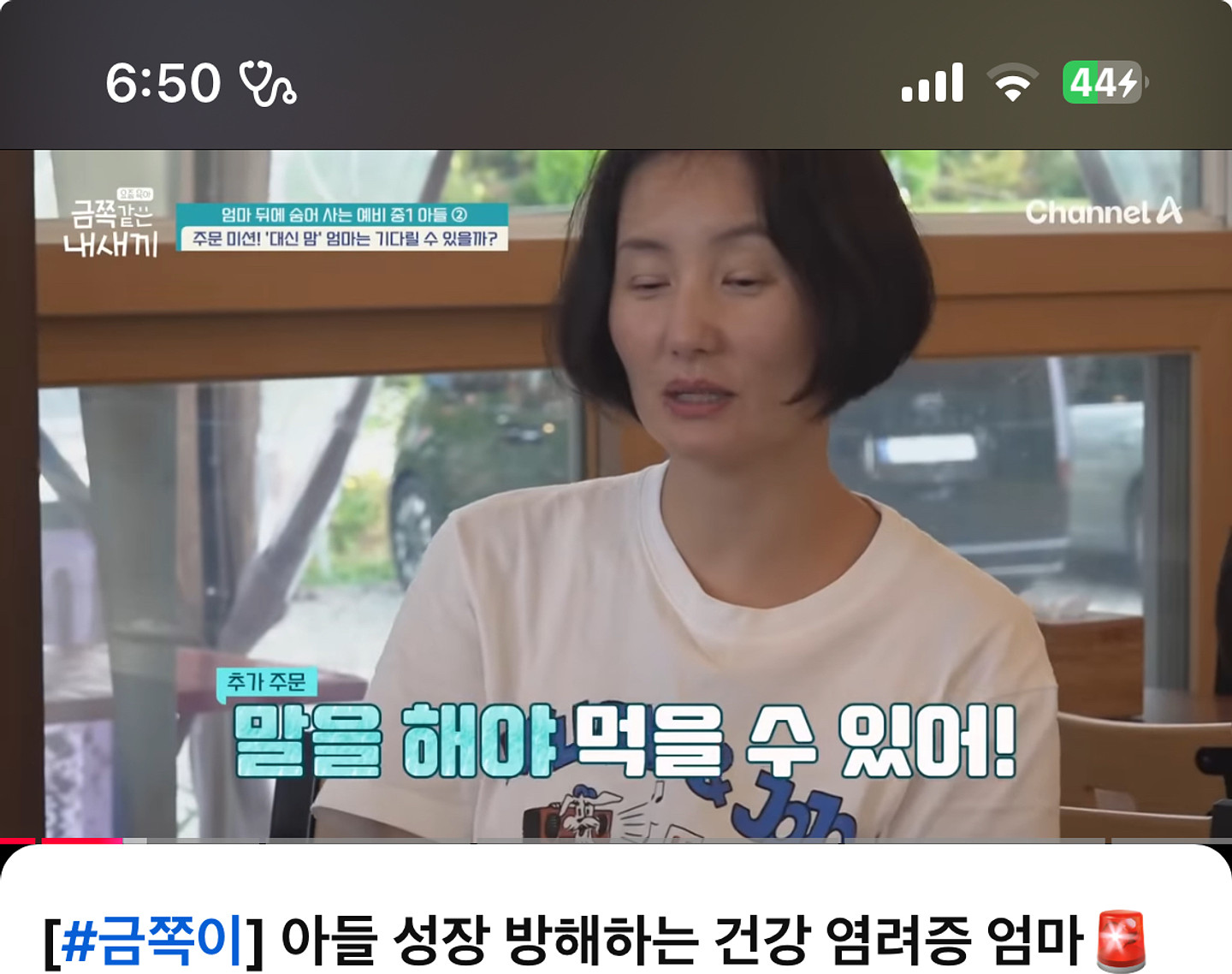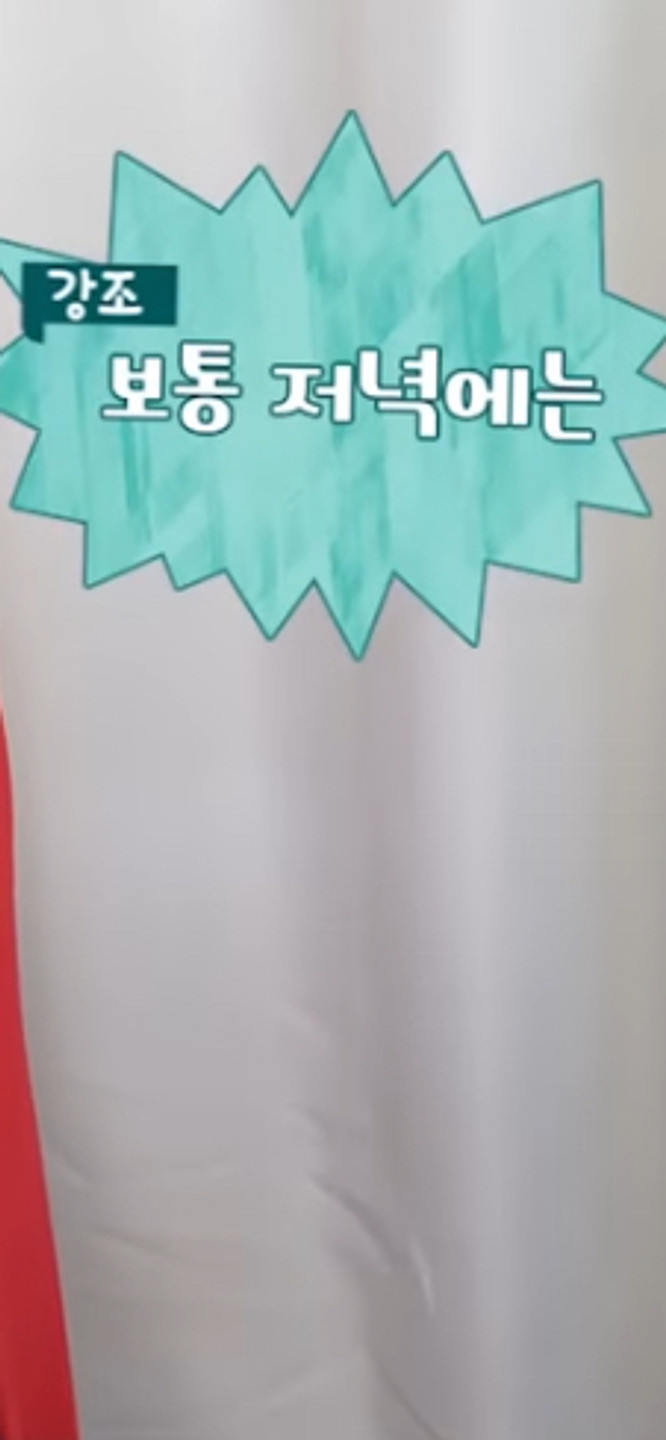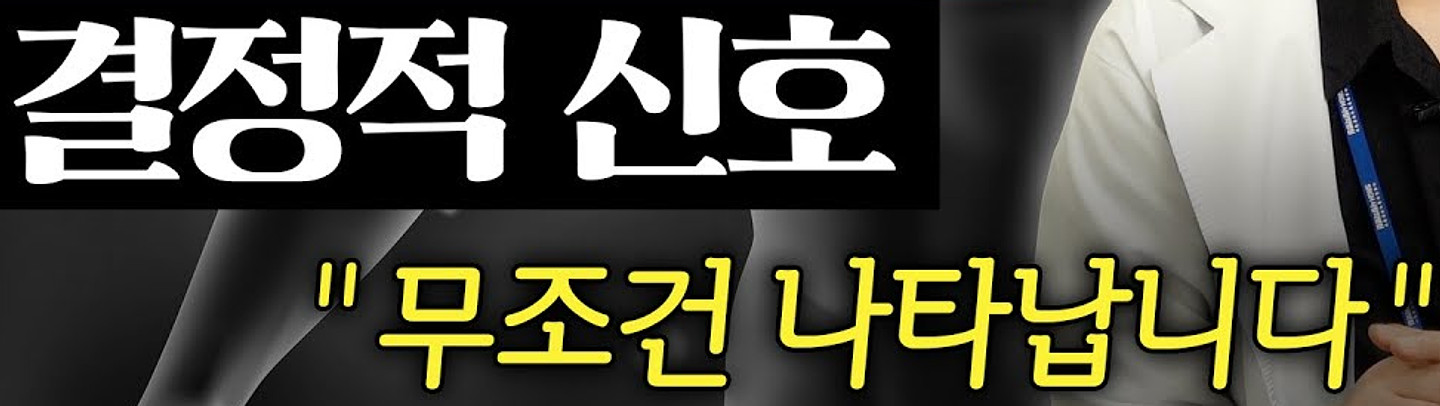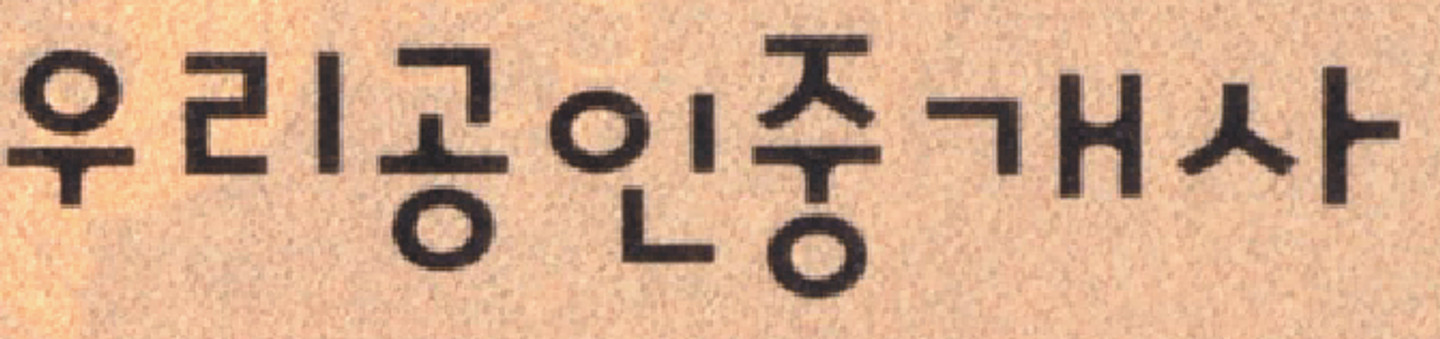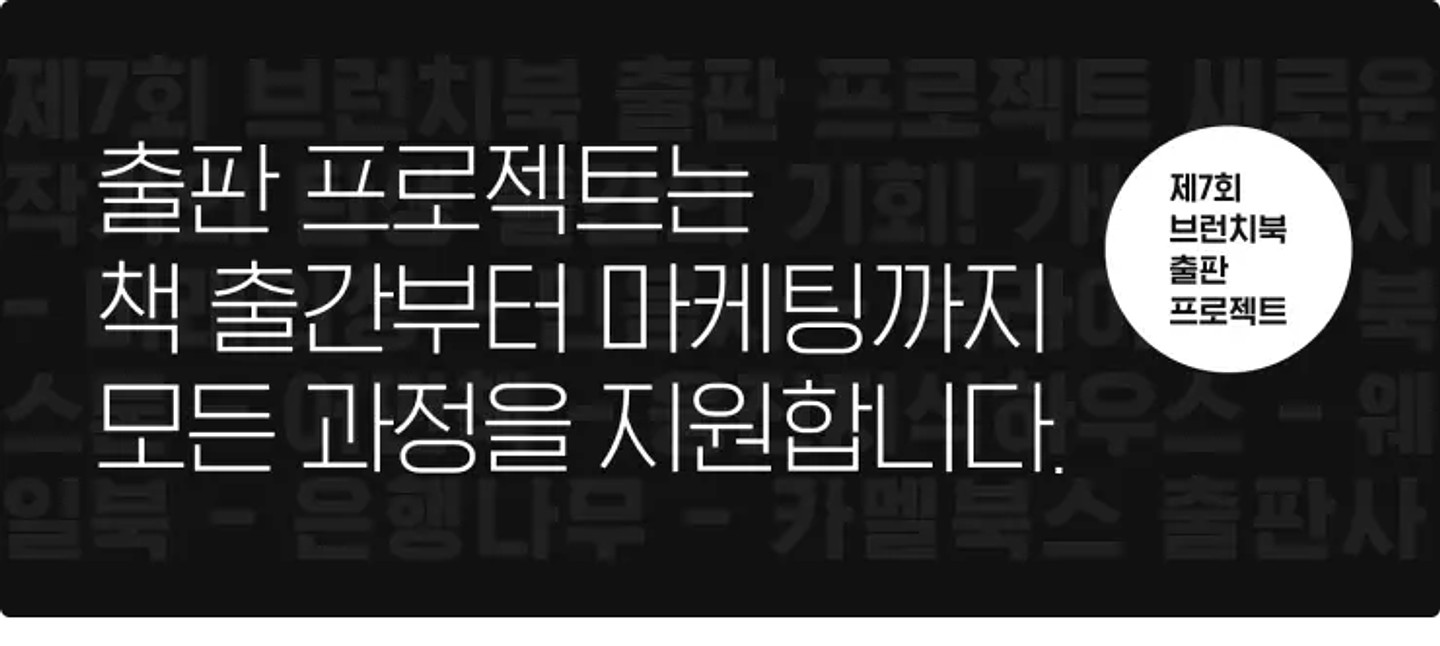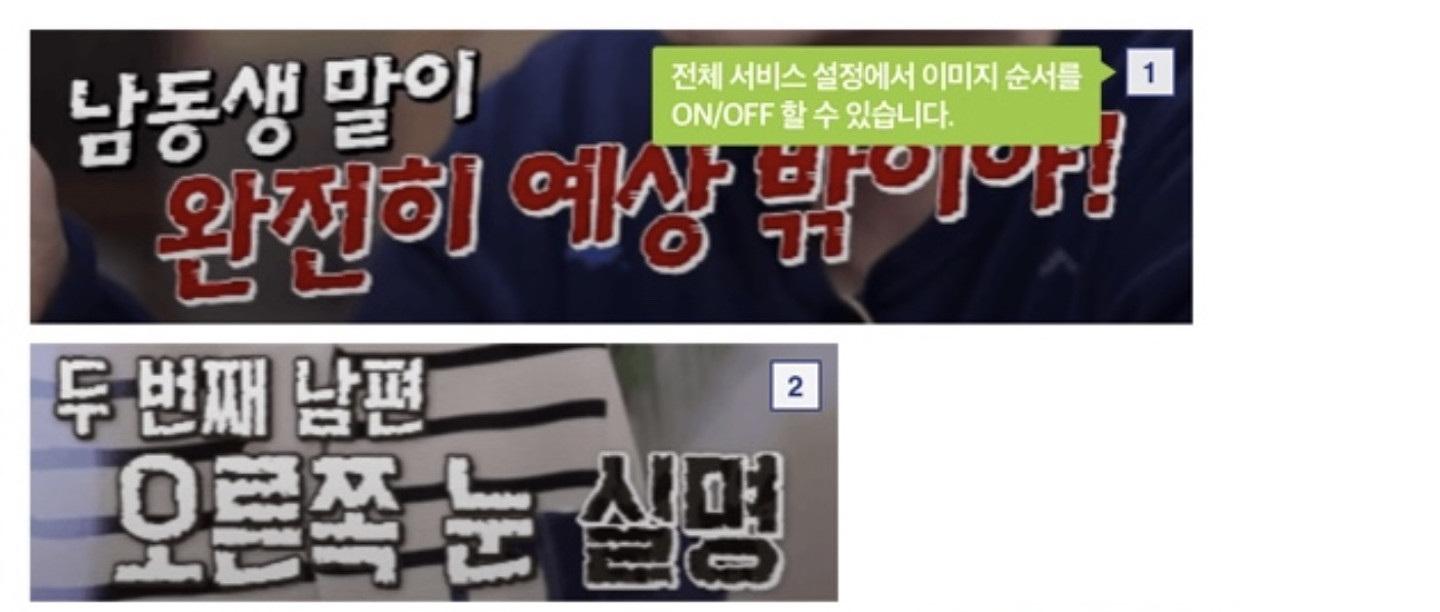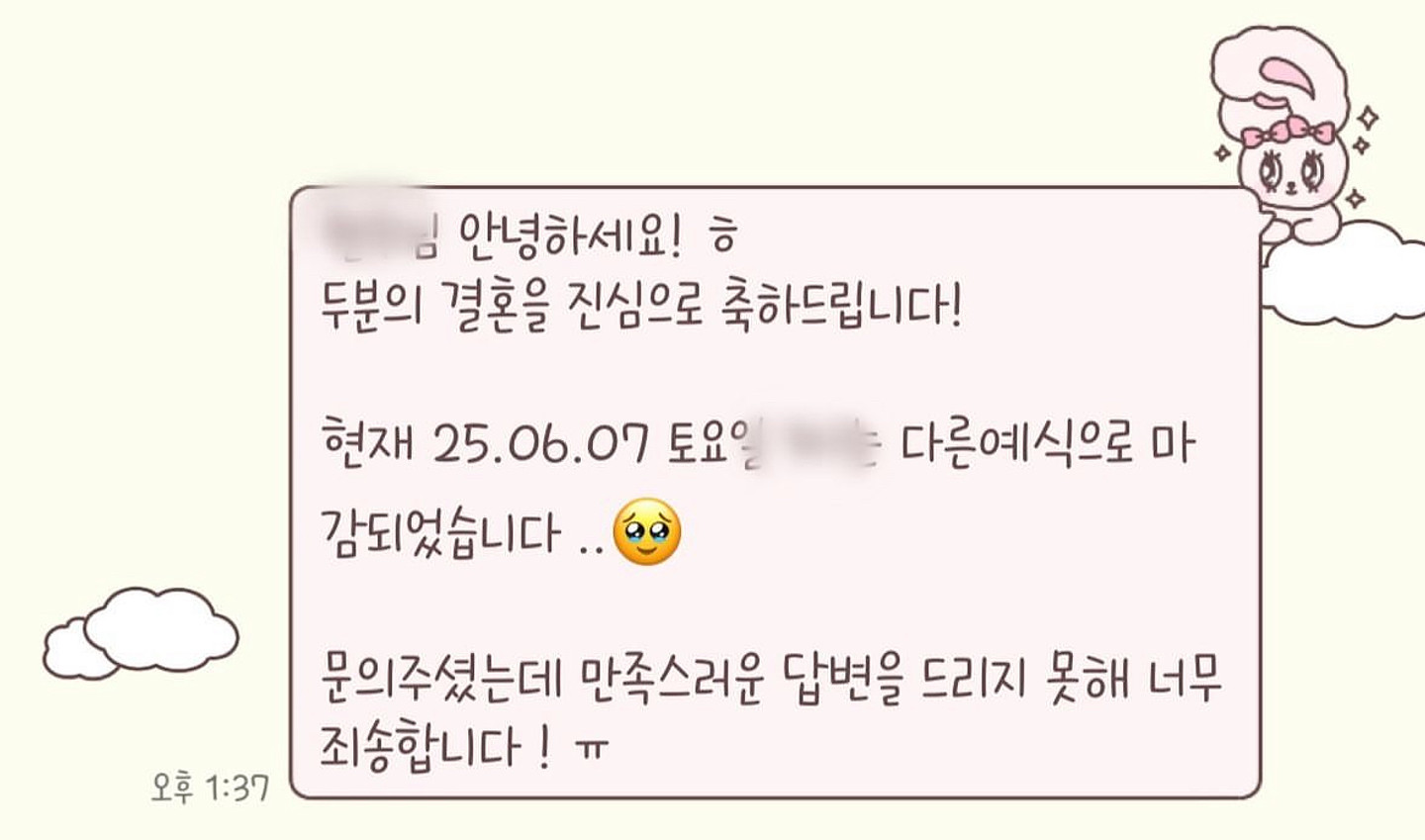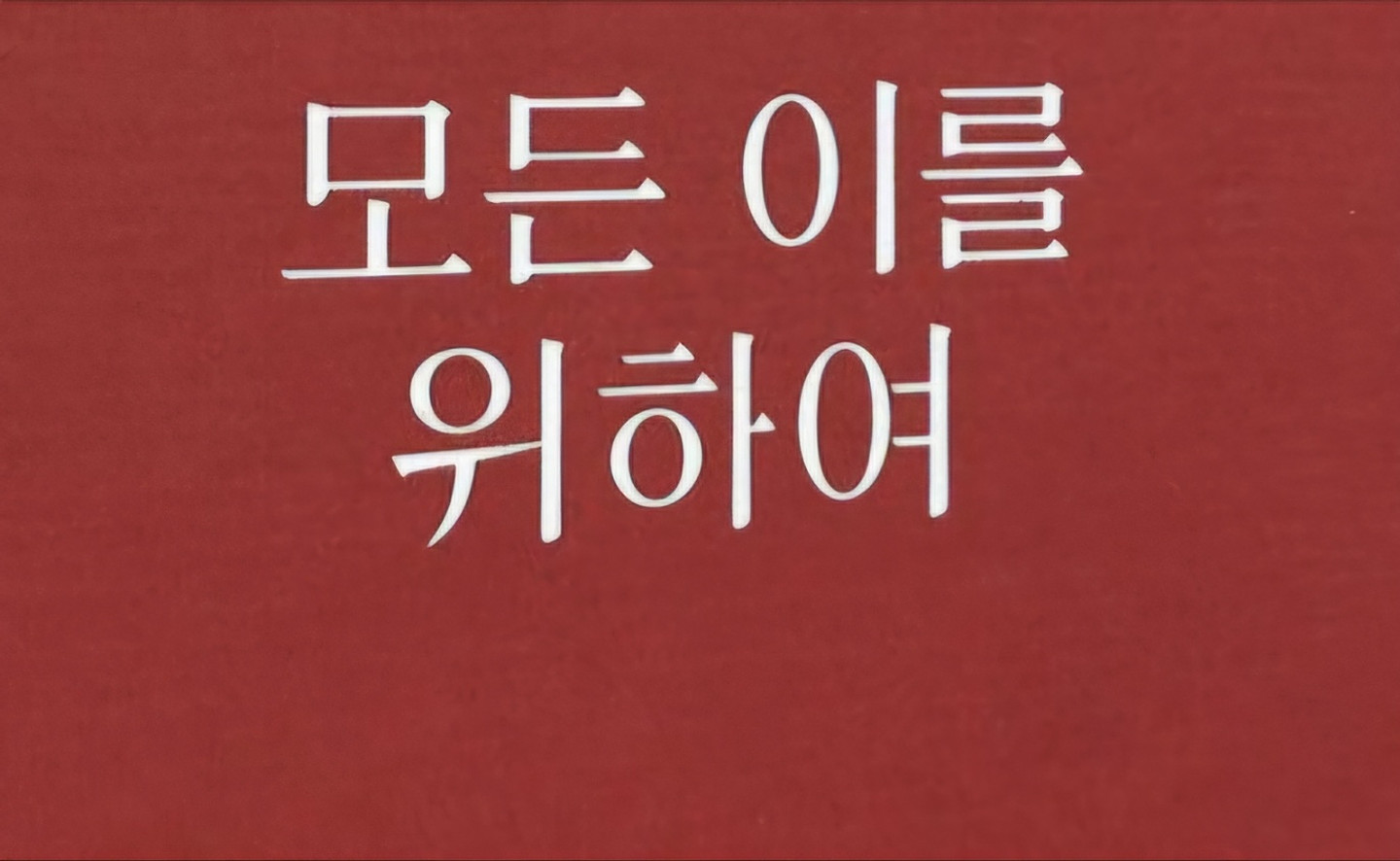
폰트 뭘까요>>
폰트 뭘까요
이거 무슨 폰트인지 알수있을까용 ?
인터넷보다가 본 짤인데 폰트가 너무 예뻐서 찾고싶어요
이건 무슨 폰트인가요??
너무 찾고 싶어요..산돌 검색해보니 안나오니 다른 브랜드 같아요.무슨 폰트인가요?ㅠㅠㅠ
바이오플라자 폰트 뭔가요~
이거 무슨폰트에여?
이 폰트는 무슨폰트일까요?
여기에 사용된 폰트 알려주세요ㅠㅠ
폰트가 몰까요..귀엽고 예뿌고 가독성 넘치네용
이 폰트명 알 수 있을까요?
요거 뭘까요?! ㅠㅠㅠㅠㅠ 급해용 ㅜ
인스타 썸네일에서 본 건데 이 폰트는 어떤 건가요?
무슨 폰트일까요?ㅠㅠ
해당 폰트 어떤 폰트일까요....급해요........
이 폰트 궁금합니다! 저렇게 획들이 크기가 다른 귀여운 폰트도 추천 부탁드려요!
혹시 이 폰트 뭘까요?
해당 영문 필기체 폰트가 무엇일까요... 아무리 찾아도 나오지 않네요...
무슨 폰트인지 아시는 분 계실까요?
폰트를 찾습니다 ㅠㅠ
폰트명이 고수님들 부탁드립니다
이게 무슨 폰트인가요ㅠㅜ알려주시면 정말 복 받으실거에요ㅠㅠㅠ
이거 무슨 폰트에여?
노포기에 나온 폰트인데 아시는 분 계실까요?
무슨 폰트인지 아시는 분 계신가요? 가운데는 편집한거겠죠?
이거 폰트 뭔지 아시는 분
알고 싶어요! 다운로드도 어디서 하는지!
알고 싶어요! 어디서 다운 받는지도!
이 폰트명이 뭔가요???
되게 특징적인데 ㅋ큐ㅠㅠ 못 찾고 있네요 산돌폰트 쪽인가 싶기도 하고요...
무슨 폰트일까요? 산돌 neo 시리즈랑은 미묘하게 다른듯 해 의견 구합니다
이거 폰트 어떤건지 알수있을까요? 예전에 자주 썻던건데 갑자기 이름이 생각이안나네요 ㅠㅠ 도와주세요
두산 명찰 폰트 뭔지 아시는 분 계신가요?
이 폰트 뭘까요...? 유튜브 썸네일에서 자주 보이던데. 귀여워서 궁금합니다! 도와주세용
유튜브 노래듣다가 본건데 이거 한글 무슨 폰트인가요?
이거 무슨 폰트야 ?
이름이 무엇인가요 급해요 ㅈㅂ
help me 20년전부터 있던 폰트 같은데...!!
이거 혹시 무슨 폰튼가요 대학 과제 중인데 너무 급해용
SSG 랜더스 등번호 폰트 뭔가요..? 최대한 비슷한거라도 알려주세요 ㅠㅠ
궁금해욧
무슨 폰트일까용...
안녕하세요 여기 폰트가 쥐마켓산스인줄 알았는데 아니더라구요....ㅠ 길쭉해서 자막으로 쓰기 좋은데 찾는 것을 함께 도와주실 귀인님들께 여쭙습니다 ㅠㅠ
이런 글씨체는 어디서 얻을수 있나요?? 궁금합니다 ㅠ
혹시 이 폰트 알고 계신분 계신가요?
무슨폰트일까요?? 궁금해요 알려주세요^^
출판만화 폰트인데 궁금합니다 ㅠㅠ
이 폰트 어떤 폰트일까요??
무슨폰트인지 아시는분
어떤 폰트일까요?ㅠㅠ 잘못 눌러서 폰트가 바뀌었는데 다시 찾으려니 못 찾아서요,,🥲
이건 무슨폰트인지 알려주실 수 있나요 ? ㅠㅠ